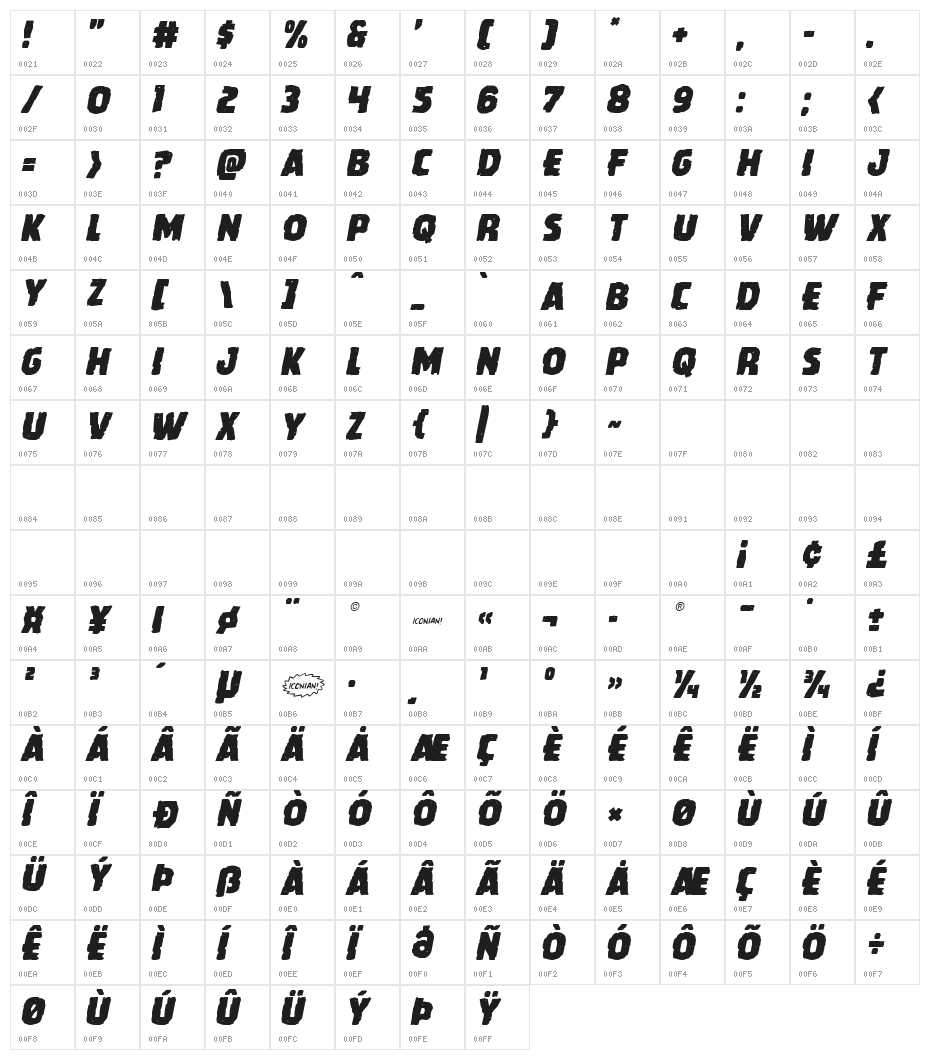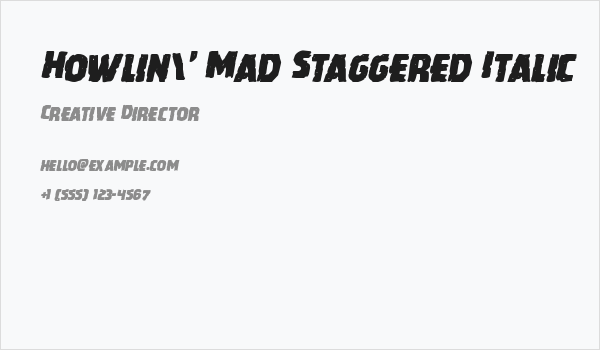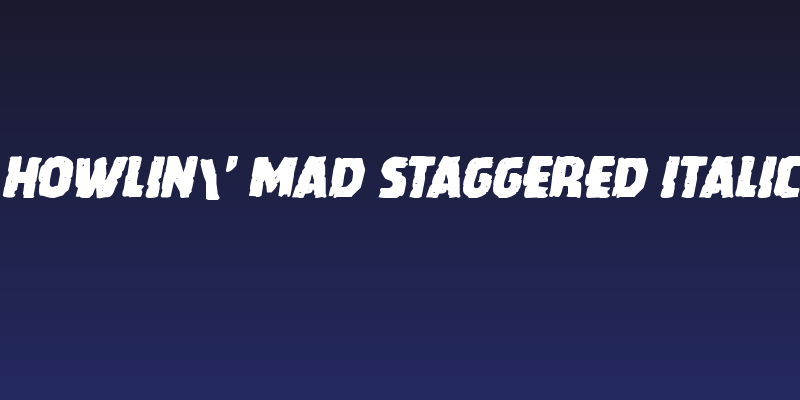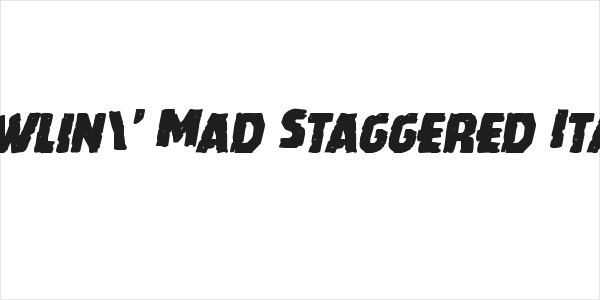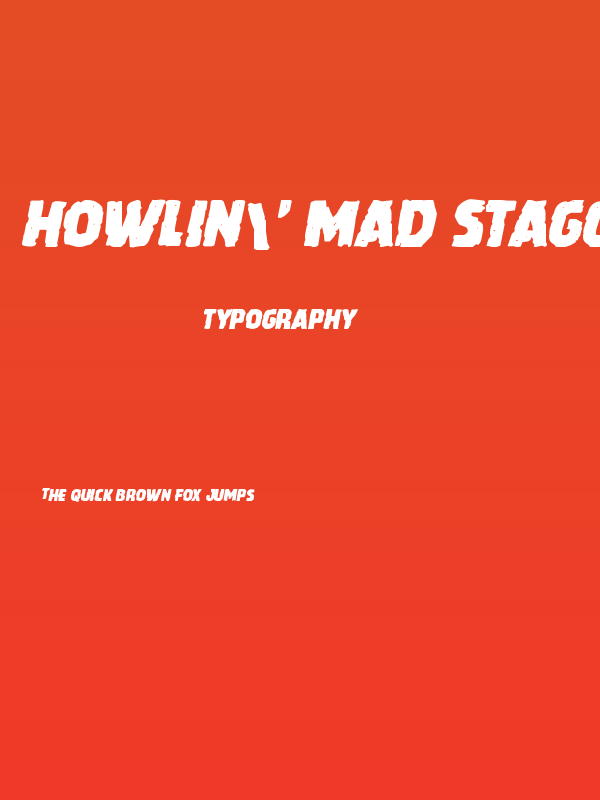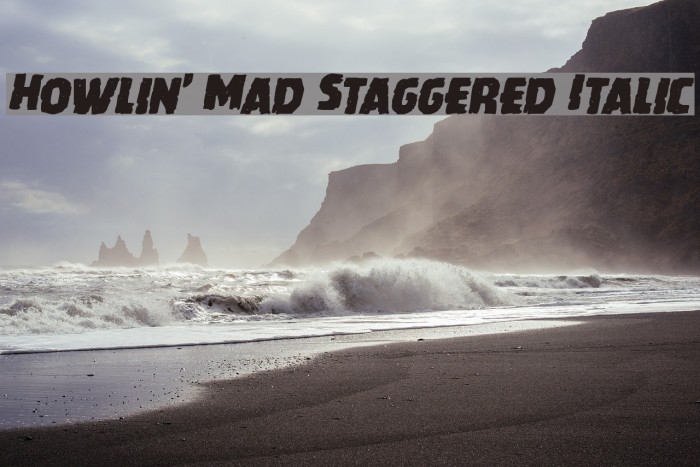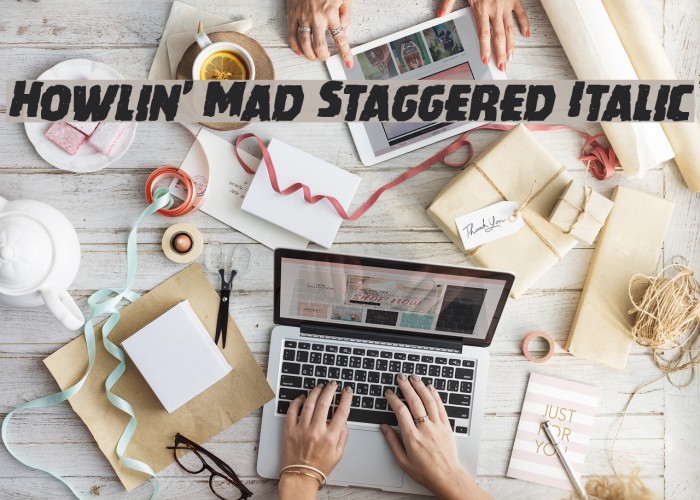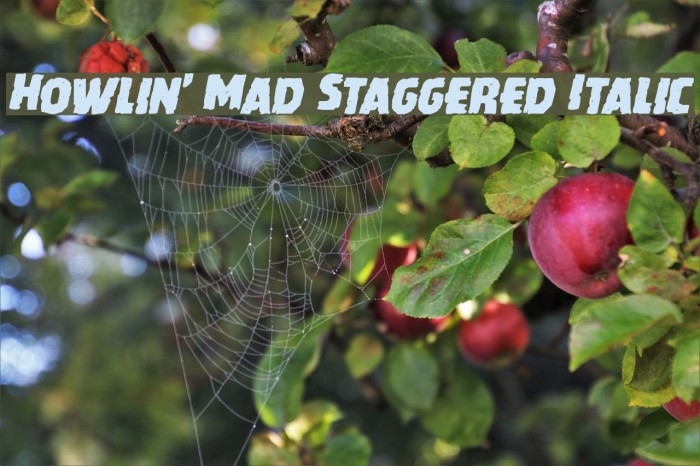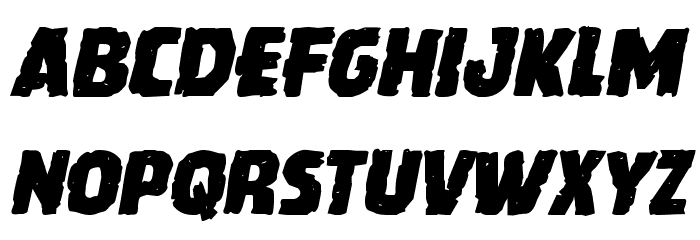
Howlin' Mad Staggered Italic Font
| Estilo general | Modern, Edgy |
| Proyectos propuestos | Ideal for posters, album covers, branding, and any design needing a bold, energetic typeface. |